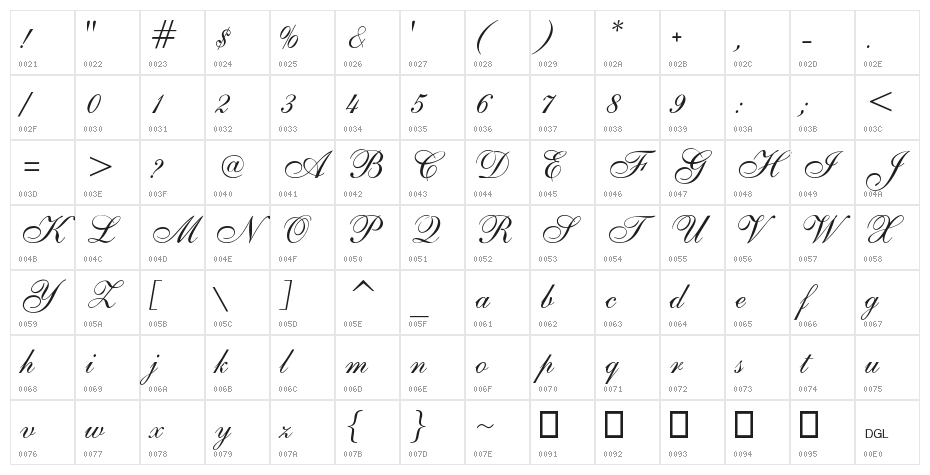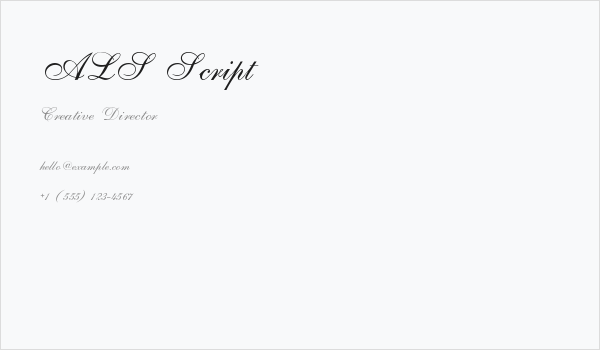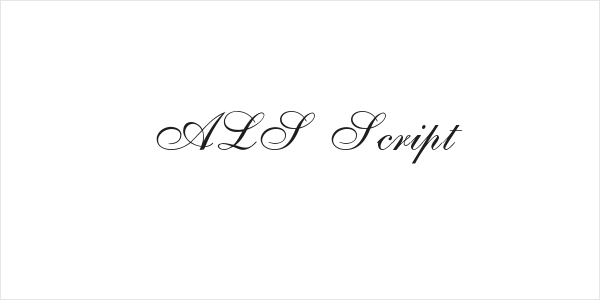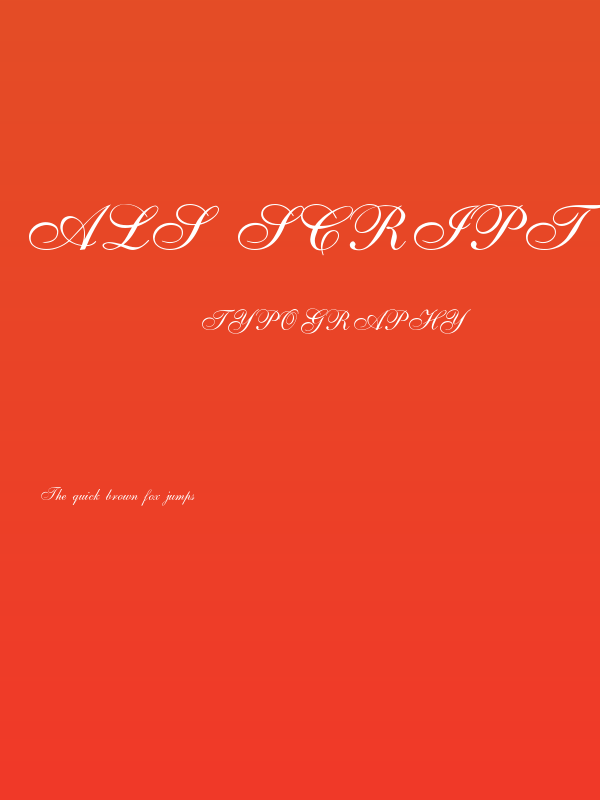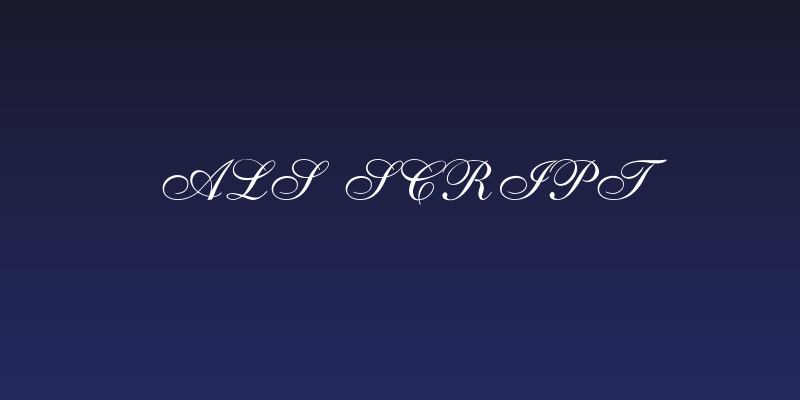
ALS Script Font
| 全体的なスタイル | Elegant, Sophisticated |
| 用途 | Logos, Invitations, Decorative text |
| おすすめプロジェクト | Ideal for wedding invitations, formal event programs, luxury brand logos, and elegant stationery design. |